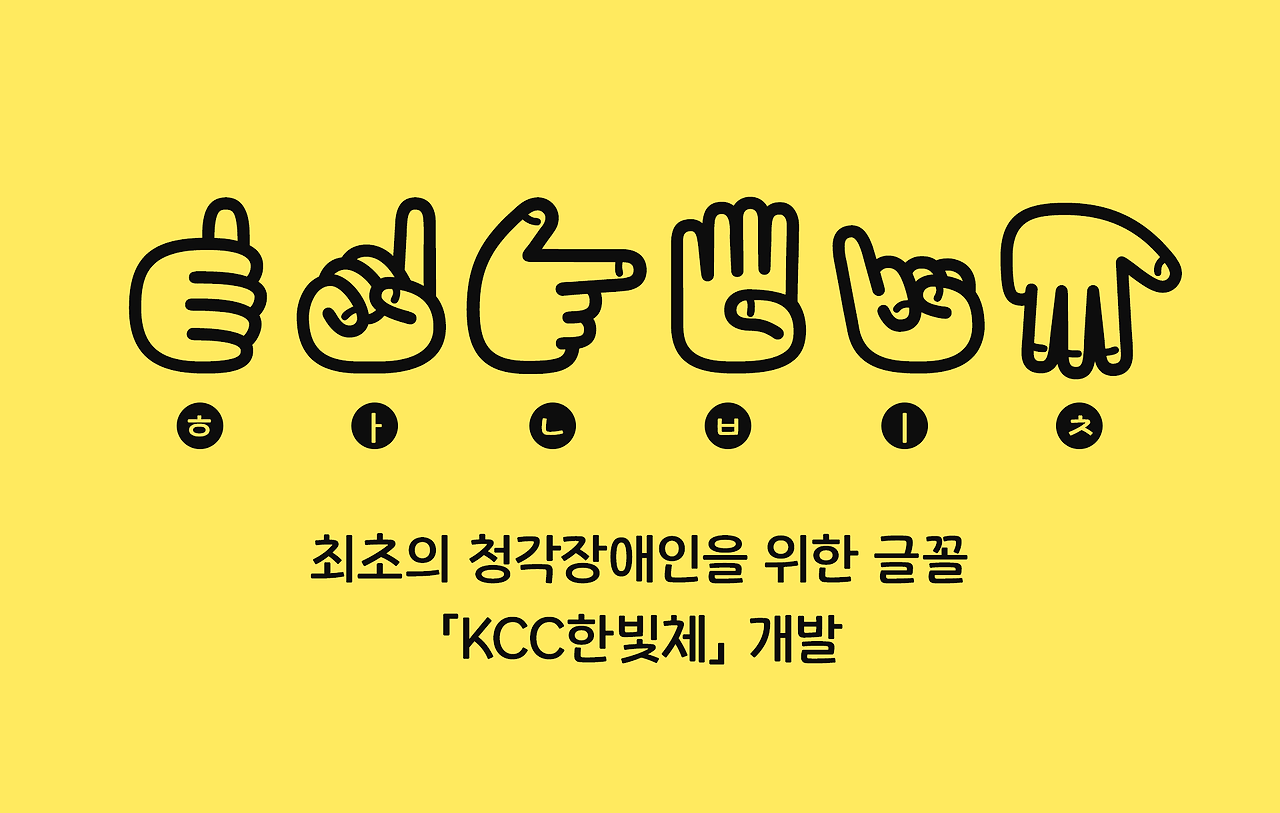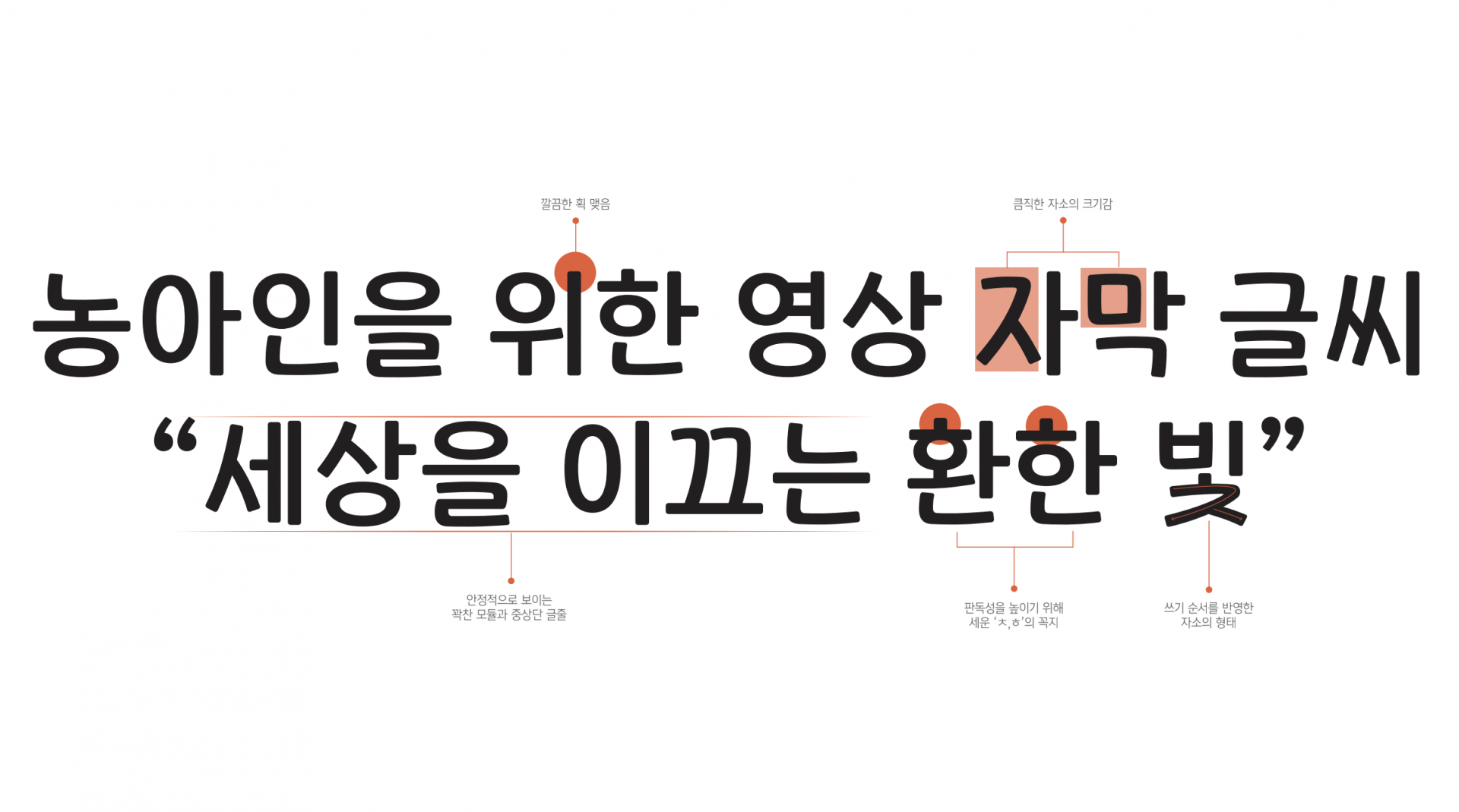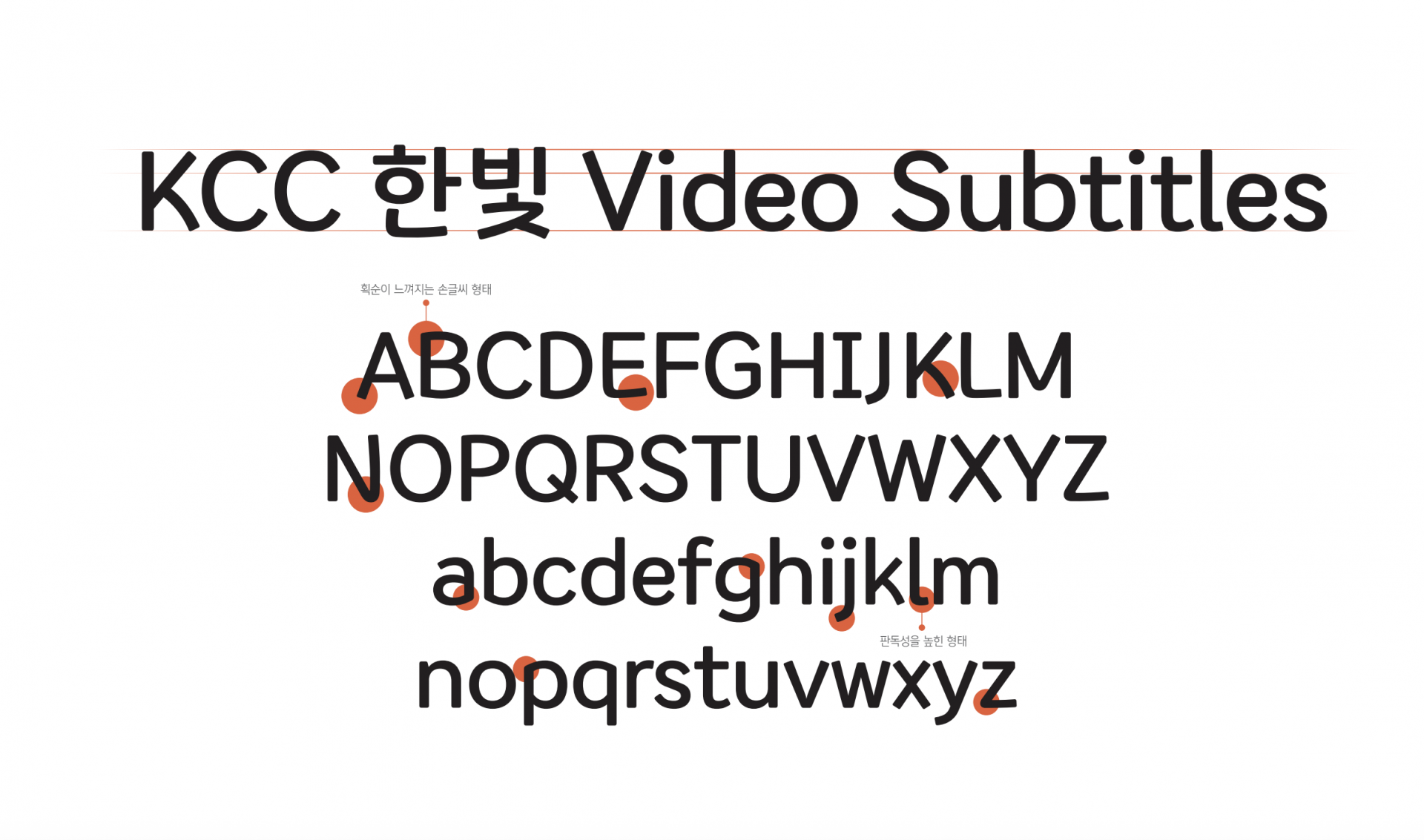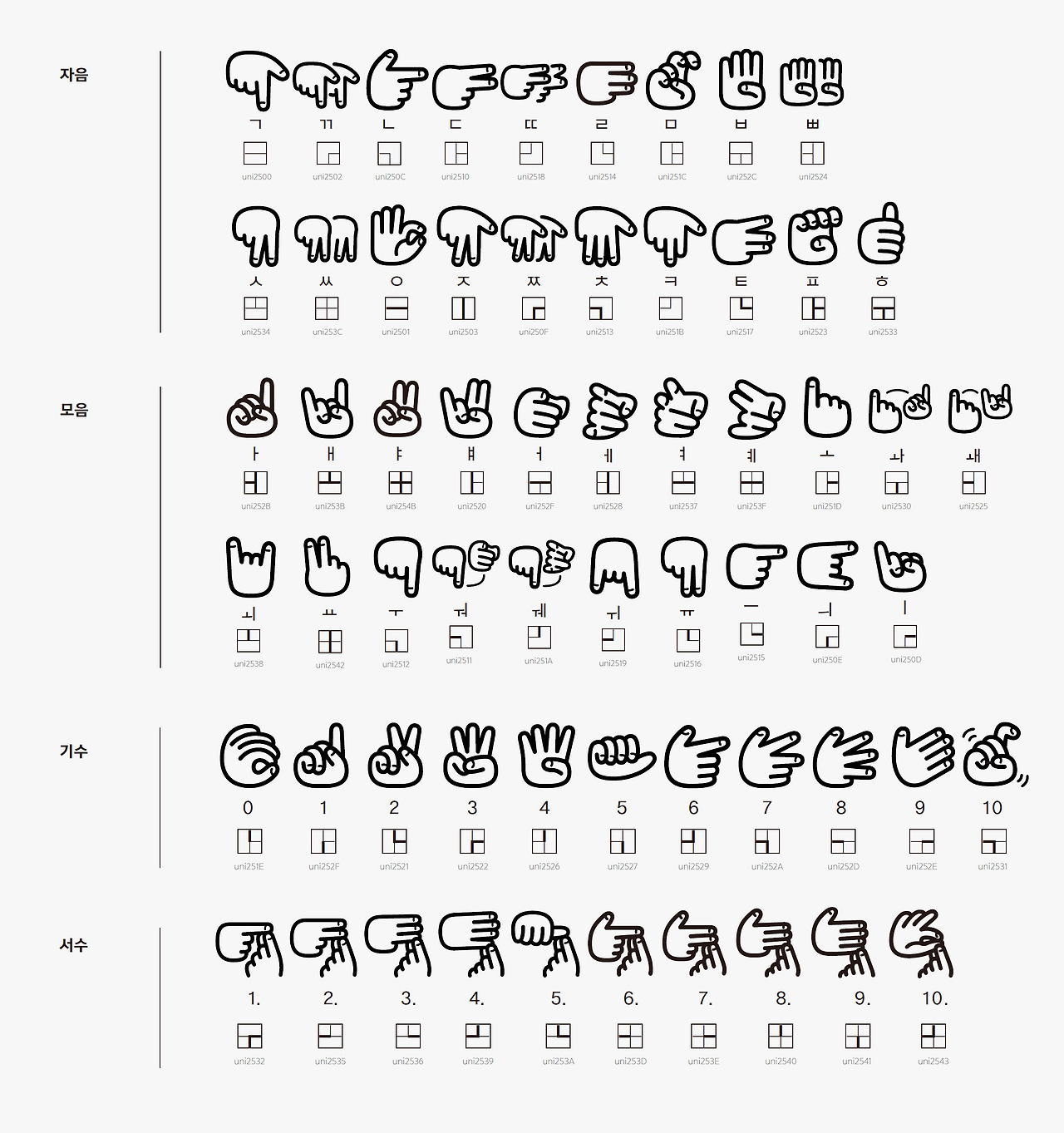
한국저작권위원회 [KCC한빛]
'한빛'은 '세상을 이끄는 환한 빛'이란 뜻의 순 우리말로, 한빛체는 최초의 청각장애인을 위한 특수문자를 마련한 영상자막용 폰트다. 2024년 2월 3일 한국 수어의 날을 맞아 공개되었으며, 수어 딩벳 특수문자를 포함하여 청각장애인이 더욱 쉽고 편하게 읽을 수 있도록 디자인하였다. 한글은 손글씨의 형태를 담아 친근한 인상을 더했다.
포함문자 | 1종 / 한글 11,172자 / 라틴 94자 / KS특수문자 986자 / 추가딩벳 61자 |